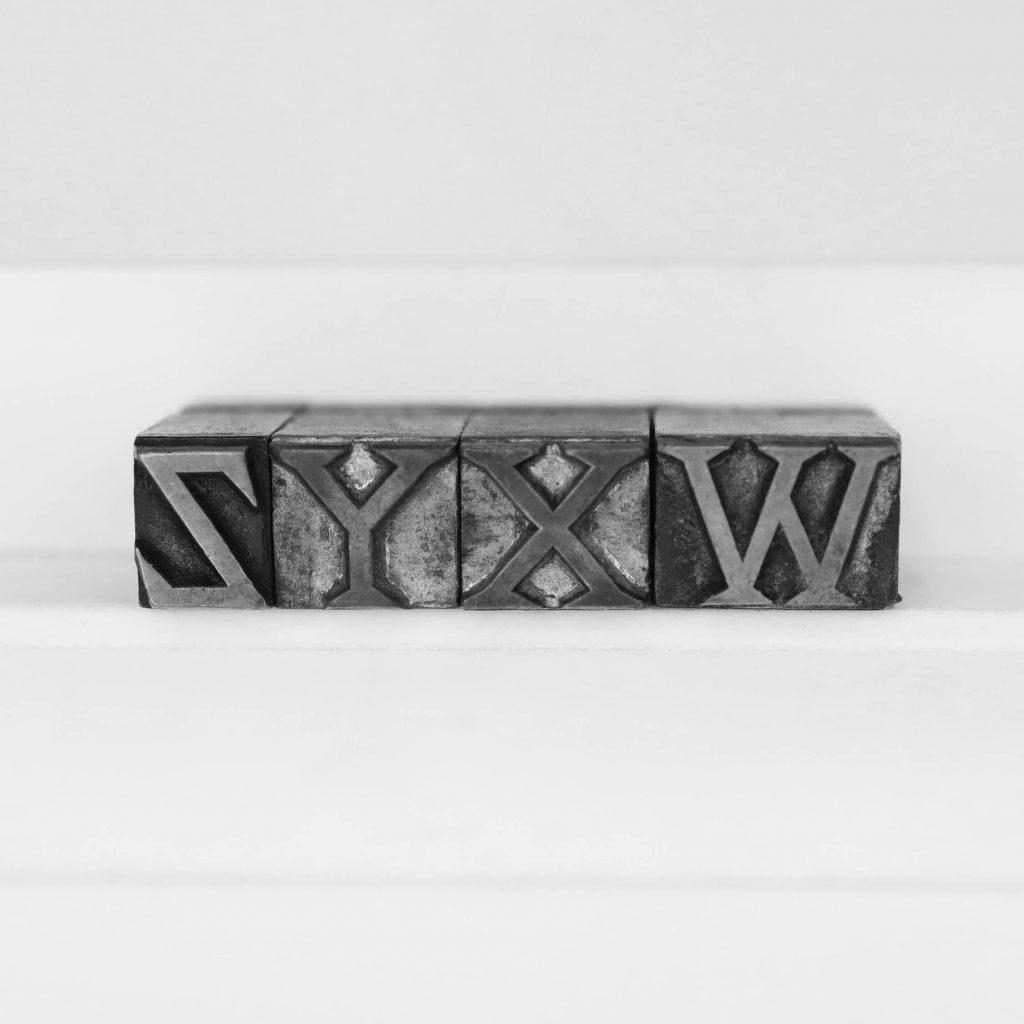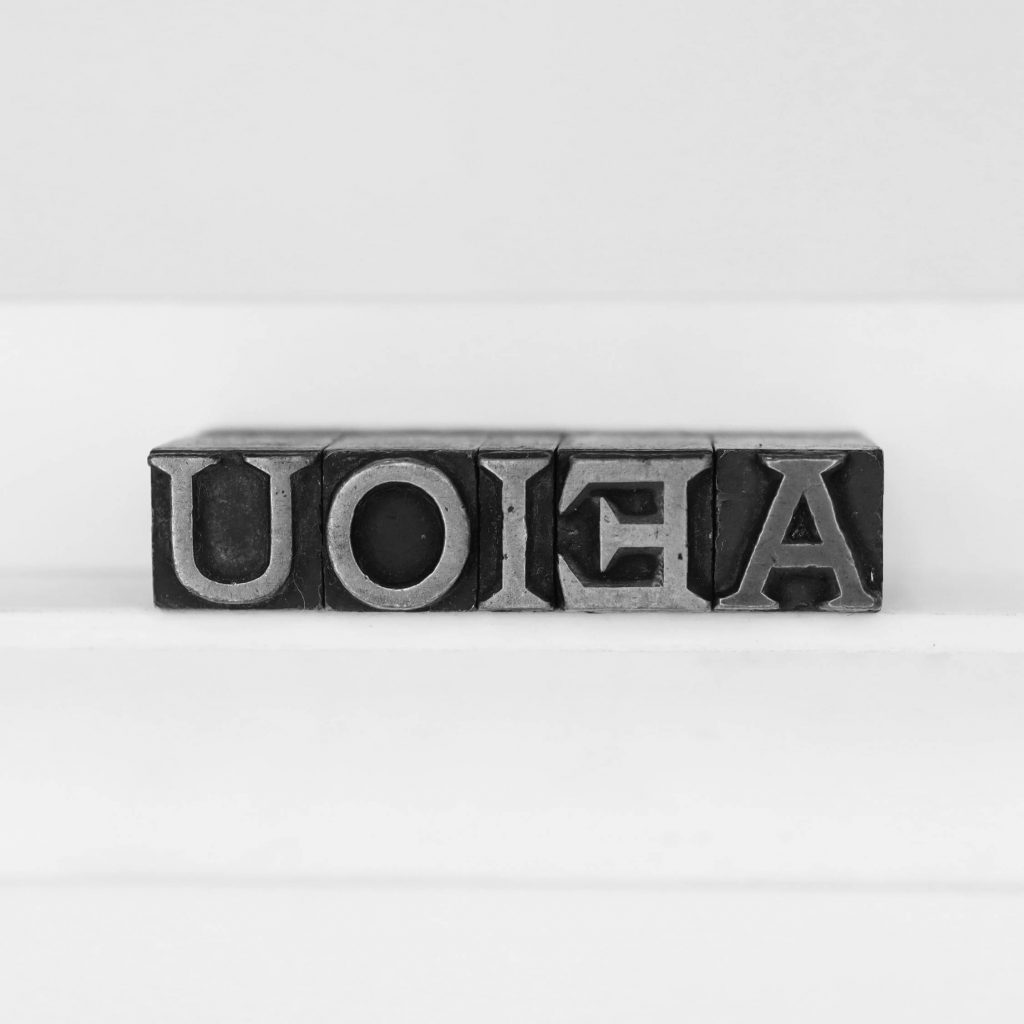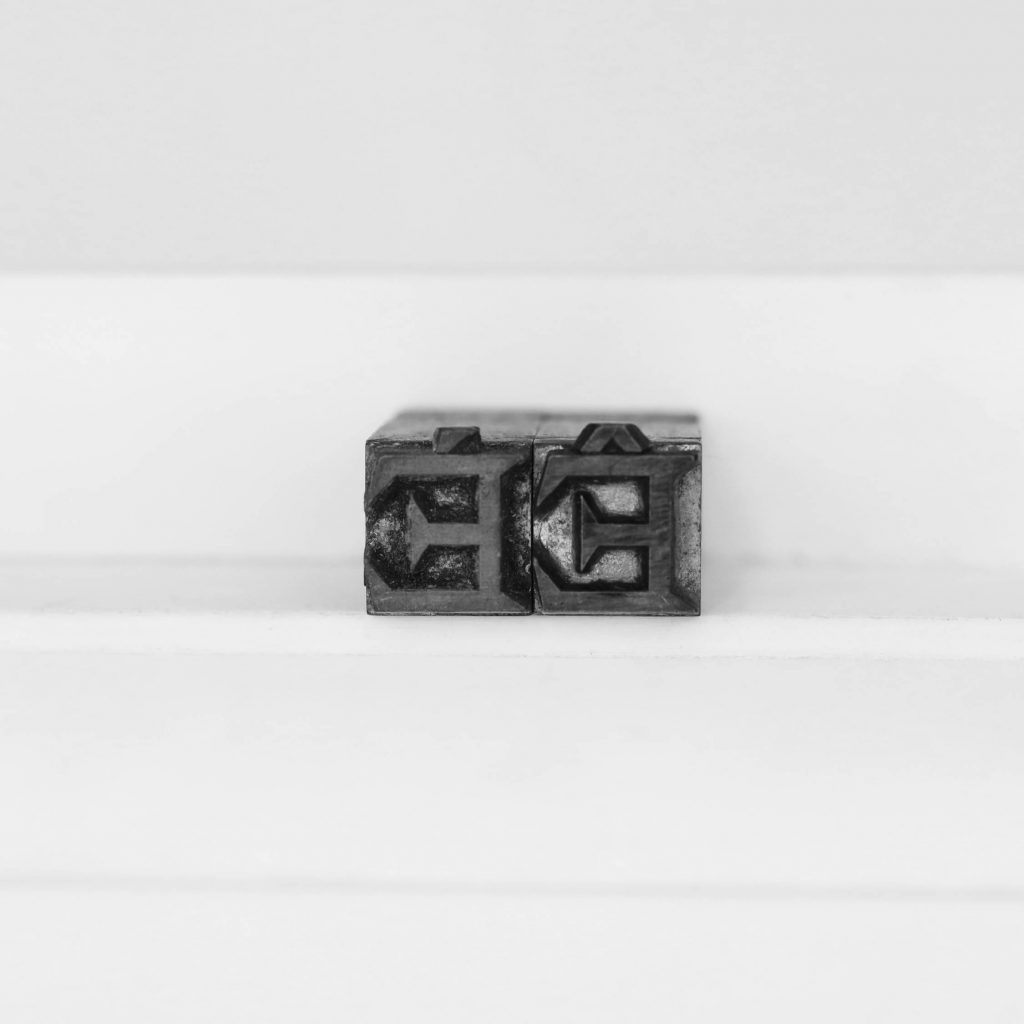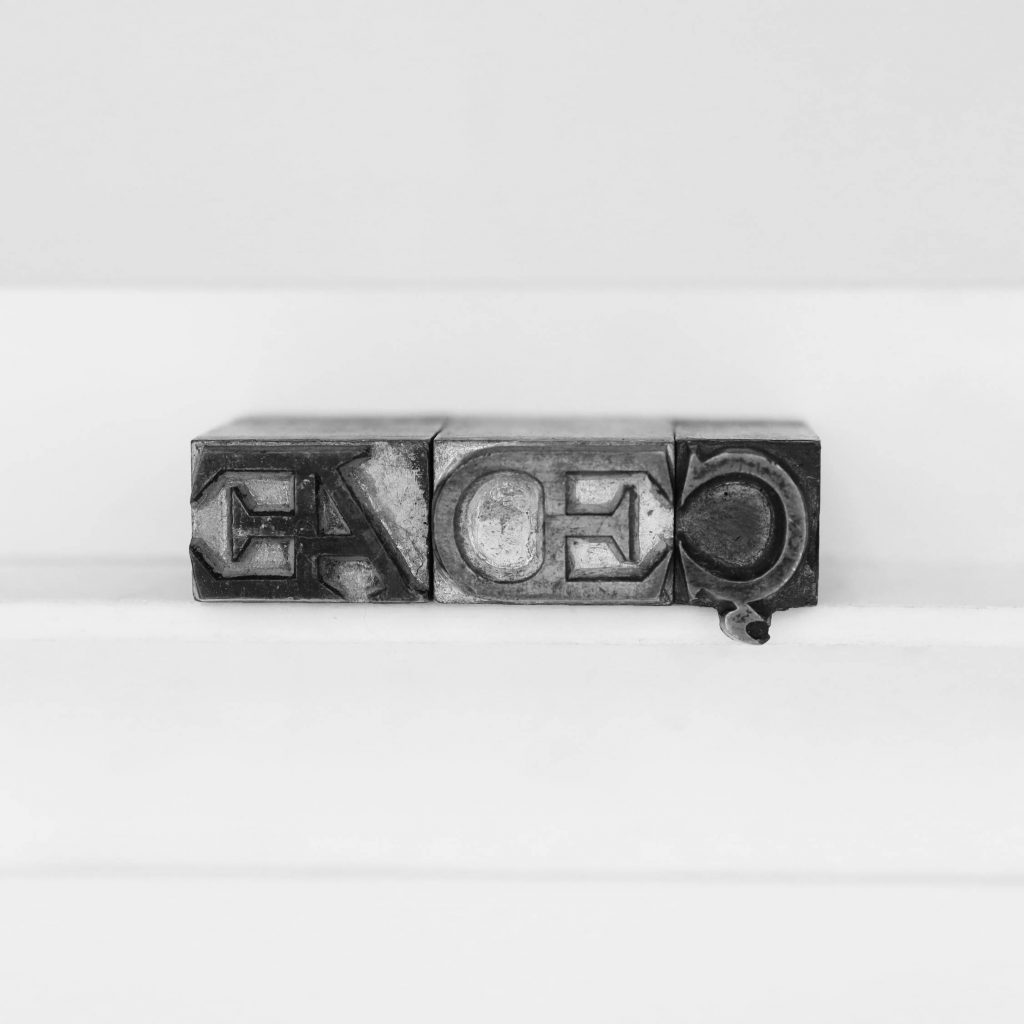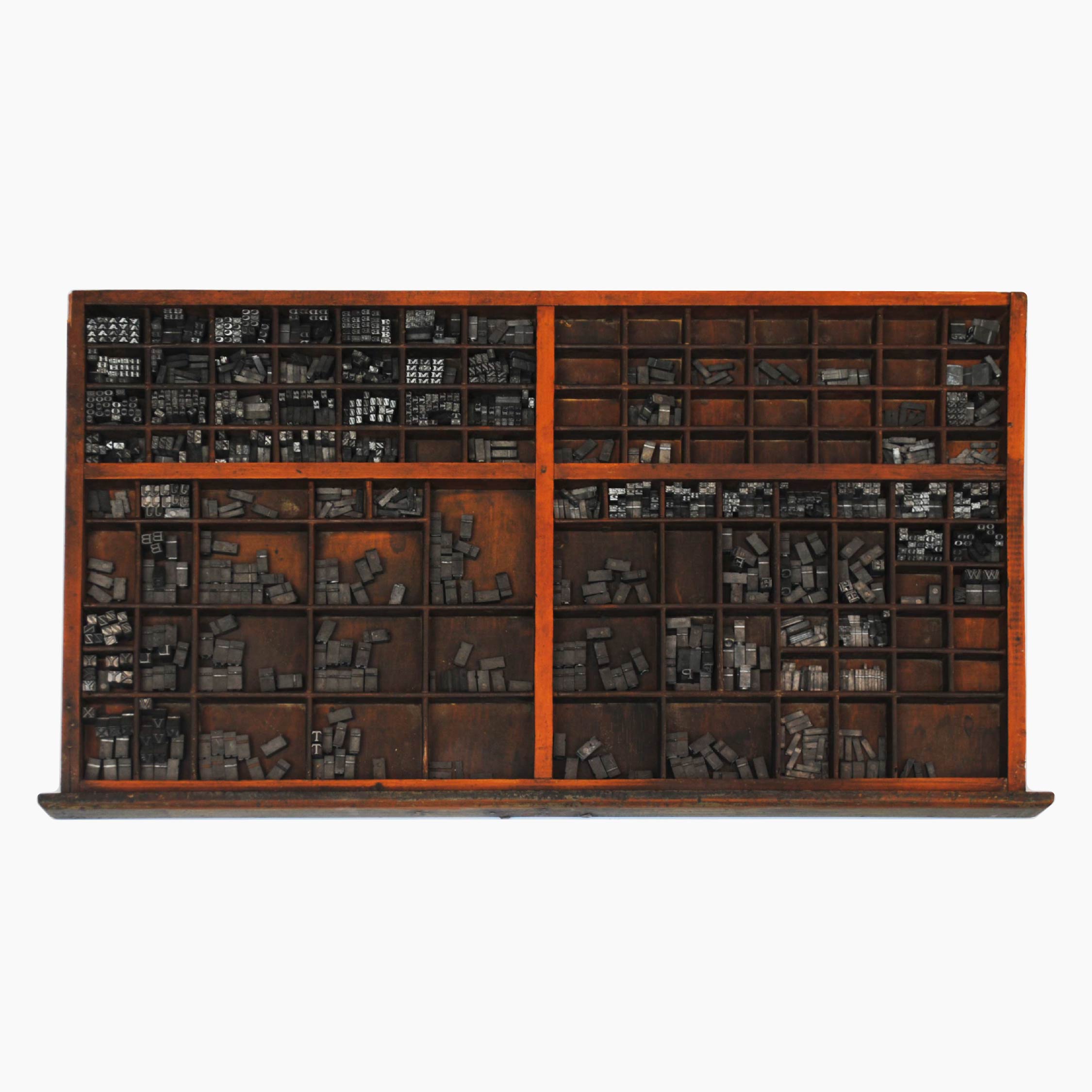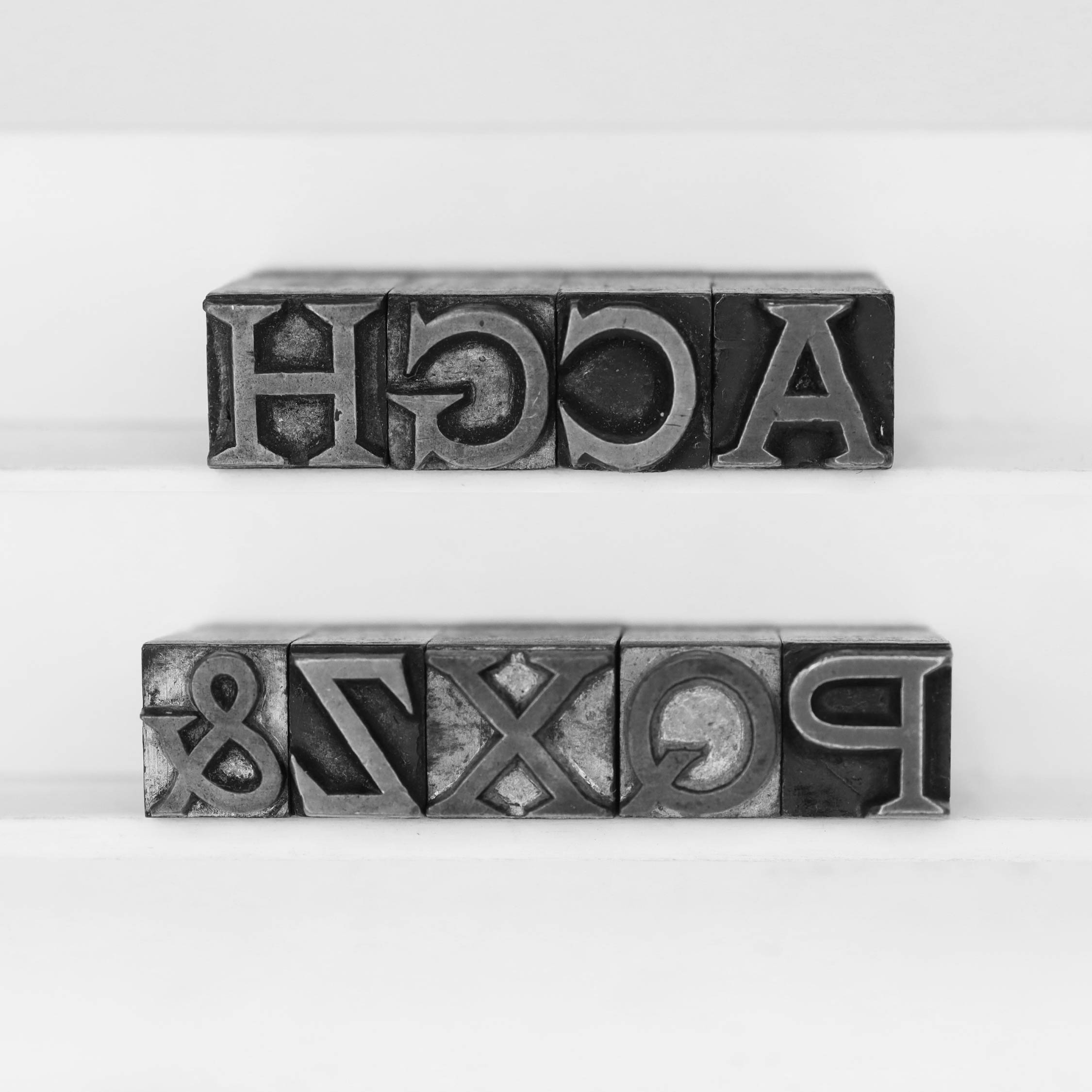
[Iniziali Rinascimento Larghe] 28 pt
Estilo
Serifada
Corpo (pt)
28
Caracteres Chave
Q
Fundidora
EPS
Catálogo
Nebiolo [ca 1900]
EPS [s.d.]
Tipo de Inscrição
Marca de fundidora
Localização da Inscrição
Face direita
Estado de Conservação
Marcas de uso recorrente; alguns tipos apresentam desgaste na face que pode comprometer a qualidade da impressão.
Quantidade Total de Tipos
327
Disponibilidade
Maiúsculas | Algumas maiúsculas acentuadas | Algumas pontuações | Caracteres especiais
Ausência de Caracteres
Não possui numerais, e as vogais "A, I, O e U" acentuadas.
História do Estilo
Uma fonte bastante semelhante a ela foi encontrada com o nome Iniziali Rinascimento Larghe no catálogo Saggio di Caratteri da fundidora italiana Nebiolo (ca 1900), porém trata-se de uma letra cuja origem do desenho da fonte não foi identificado. Na comparação digital não foi vista divergências entre o desenho das fontes. A sigla EPS, encontrada gravada nos tipos, remeta às Escolas Profissionais Salesianas, visto que sabe-se que eles possuíam uma fundição em São Paulo. Esta fonte consta no catálogo consultado (s.d., p. 16), com numeração 105.
Observações do Pesquisador
Tipos notadamente frágeis, com partes quebradas e demonstram falhas de fundição, apresentando bolhas de ar especialmente nas partes inferiores dos tipos, provavelmente causada por um erro de injeção do metal na matriz.